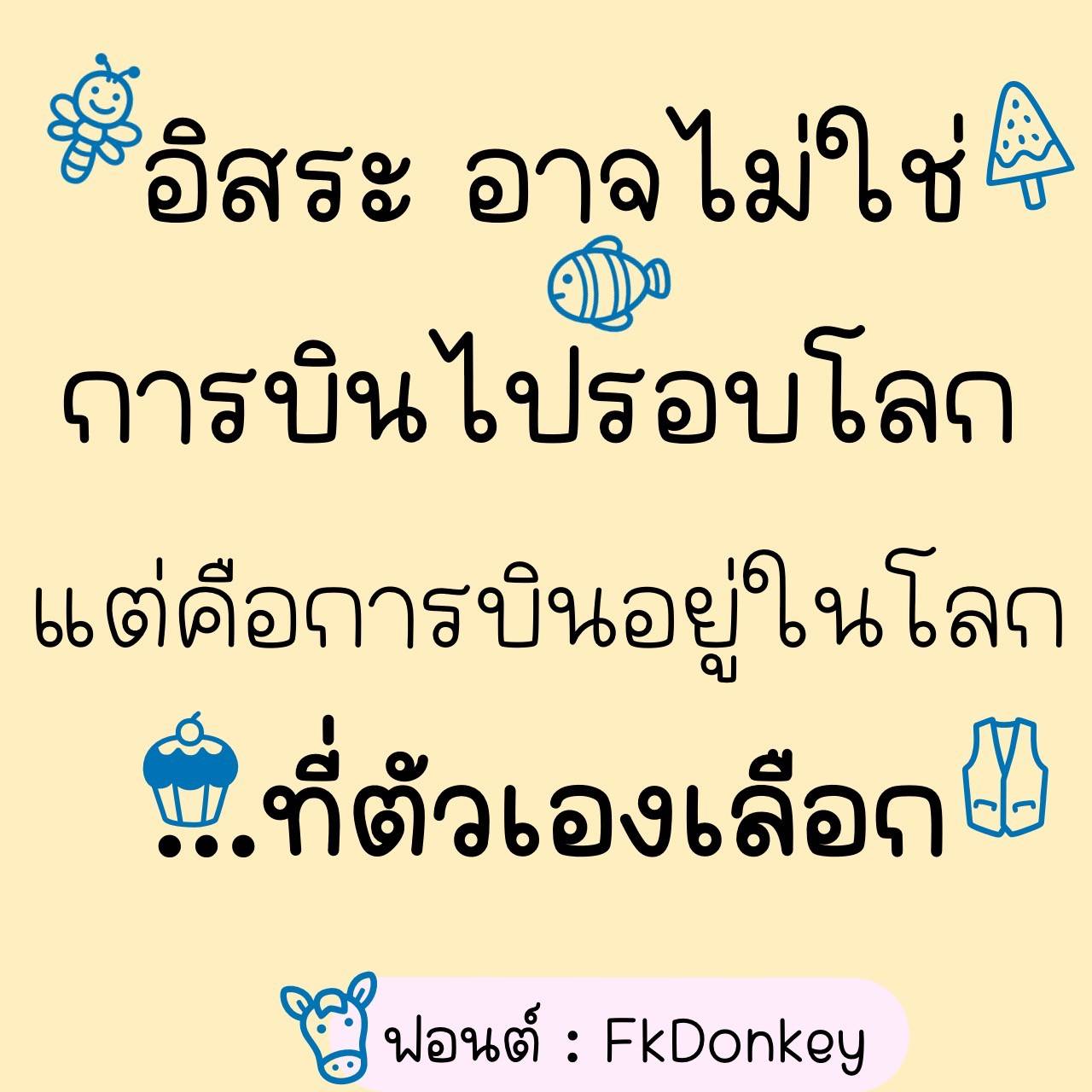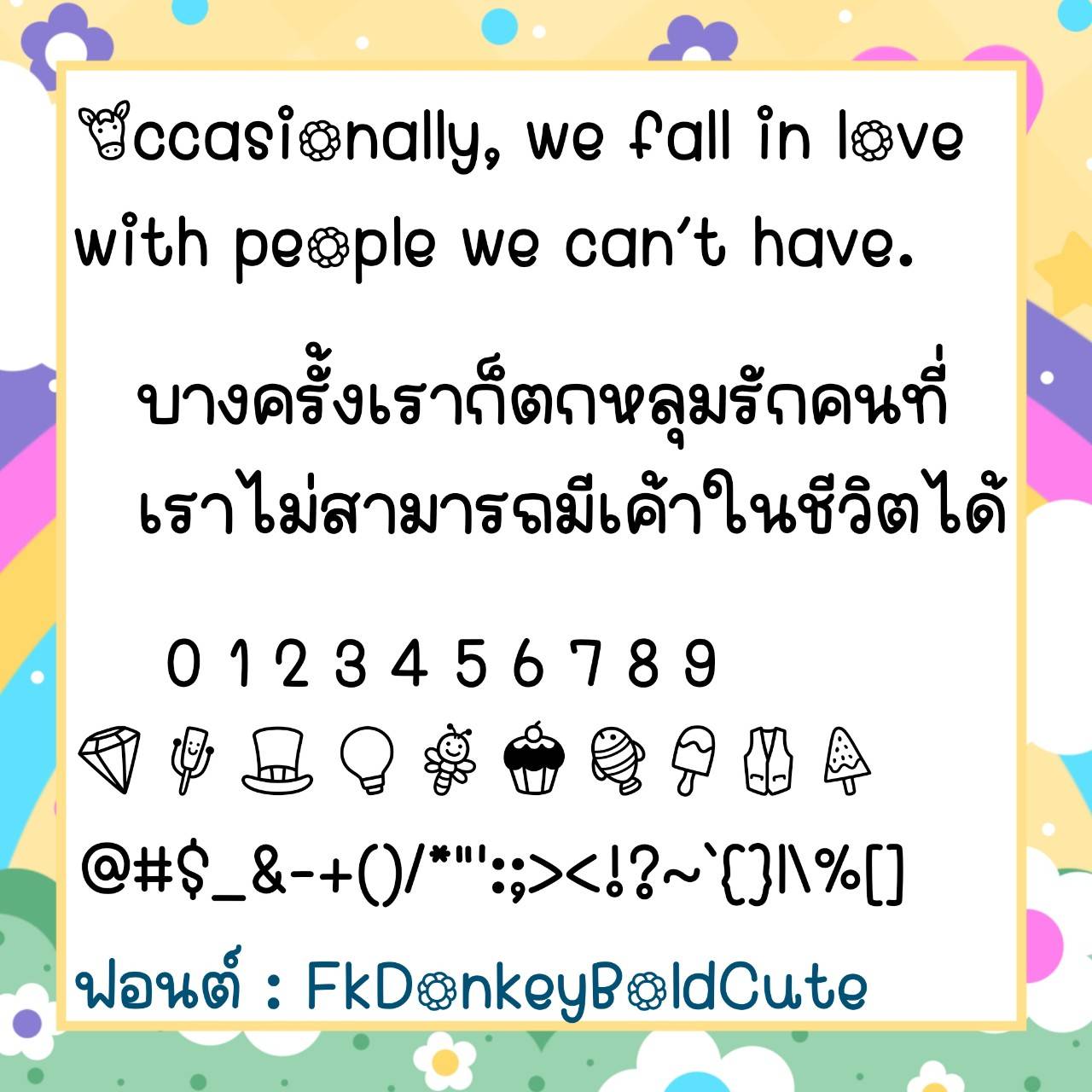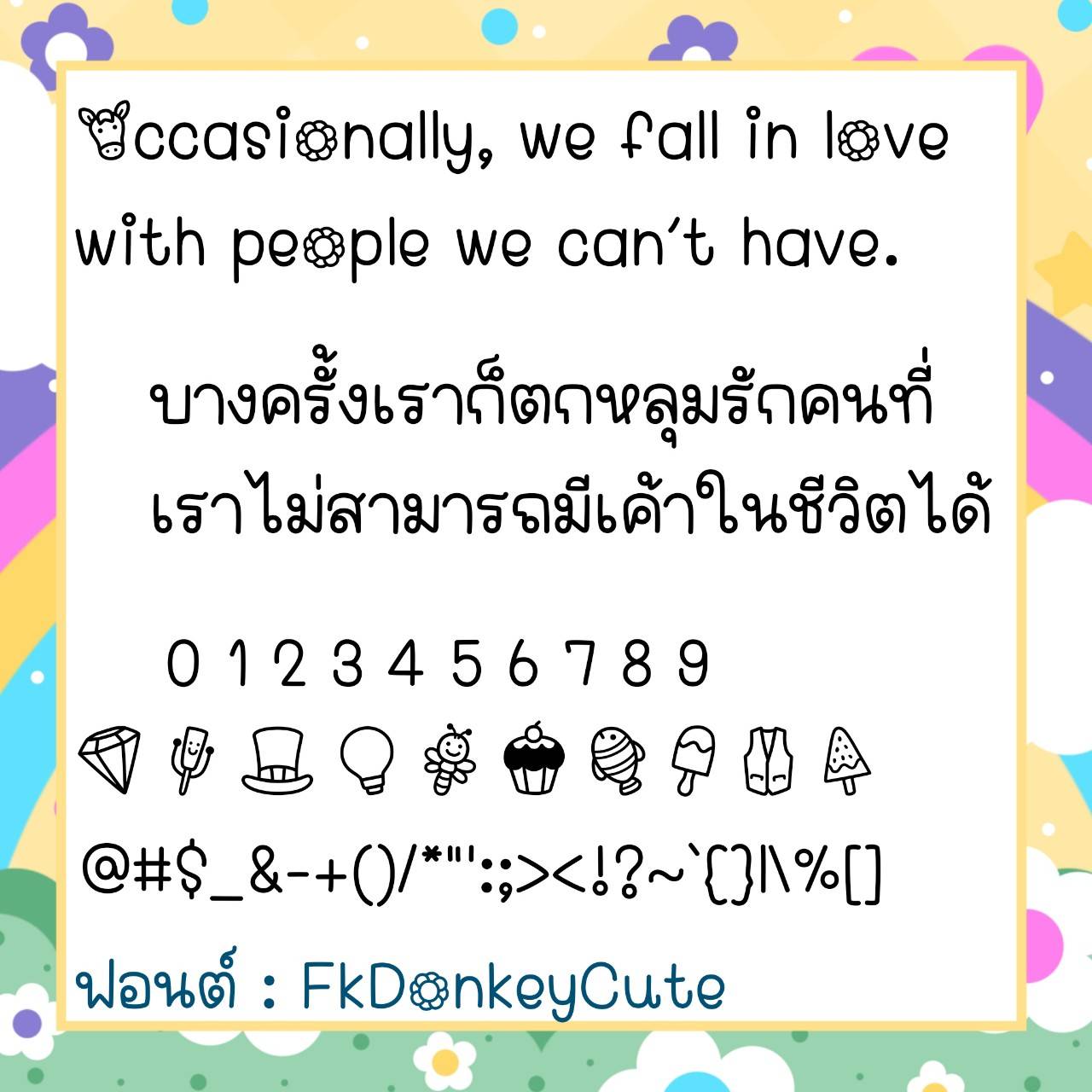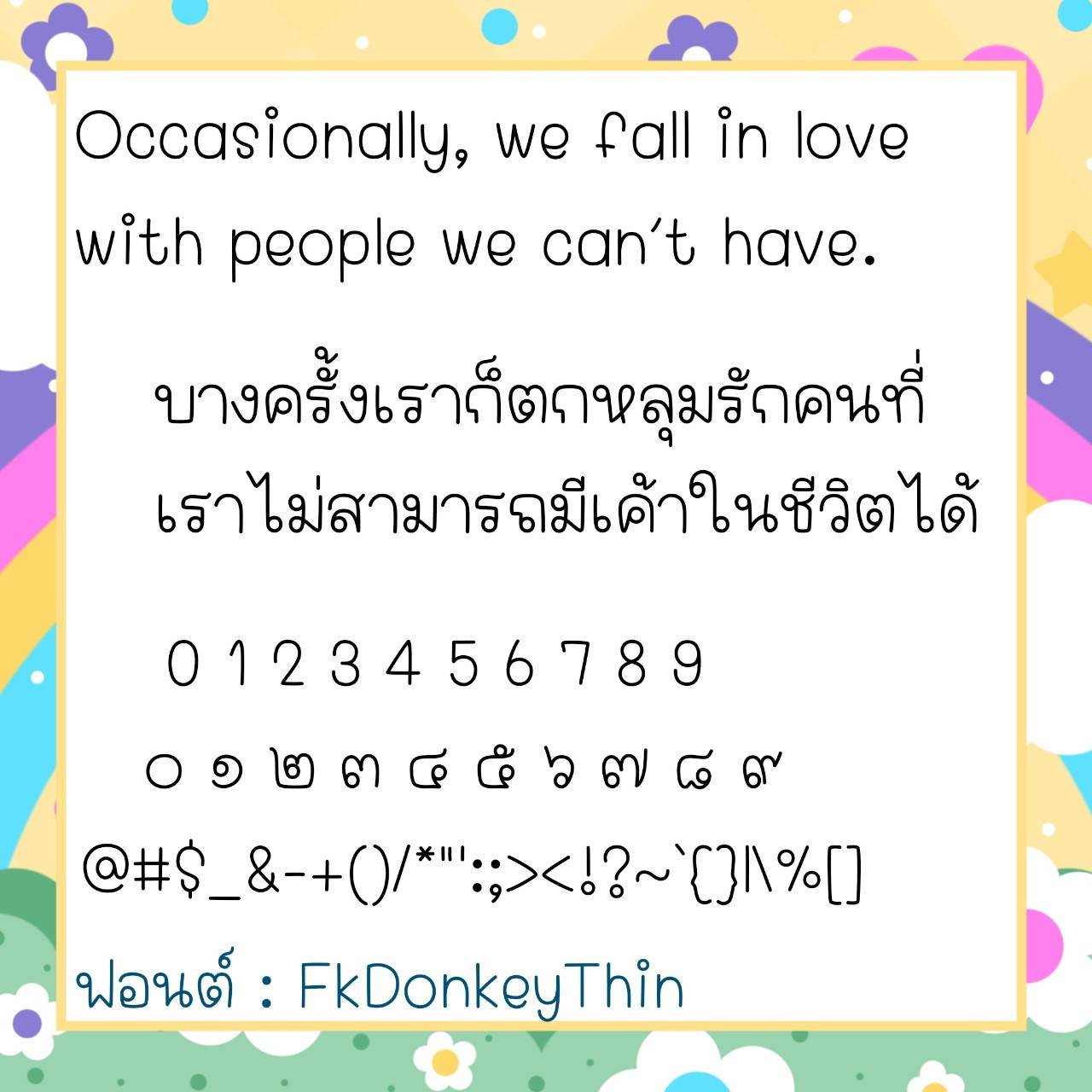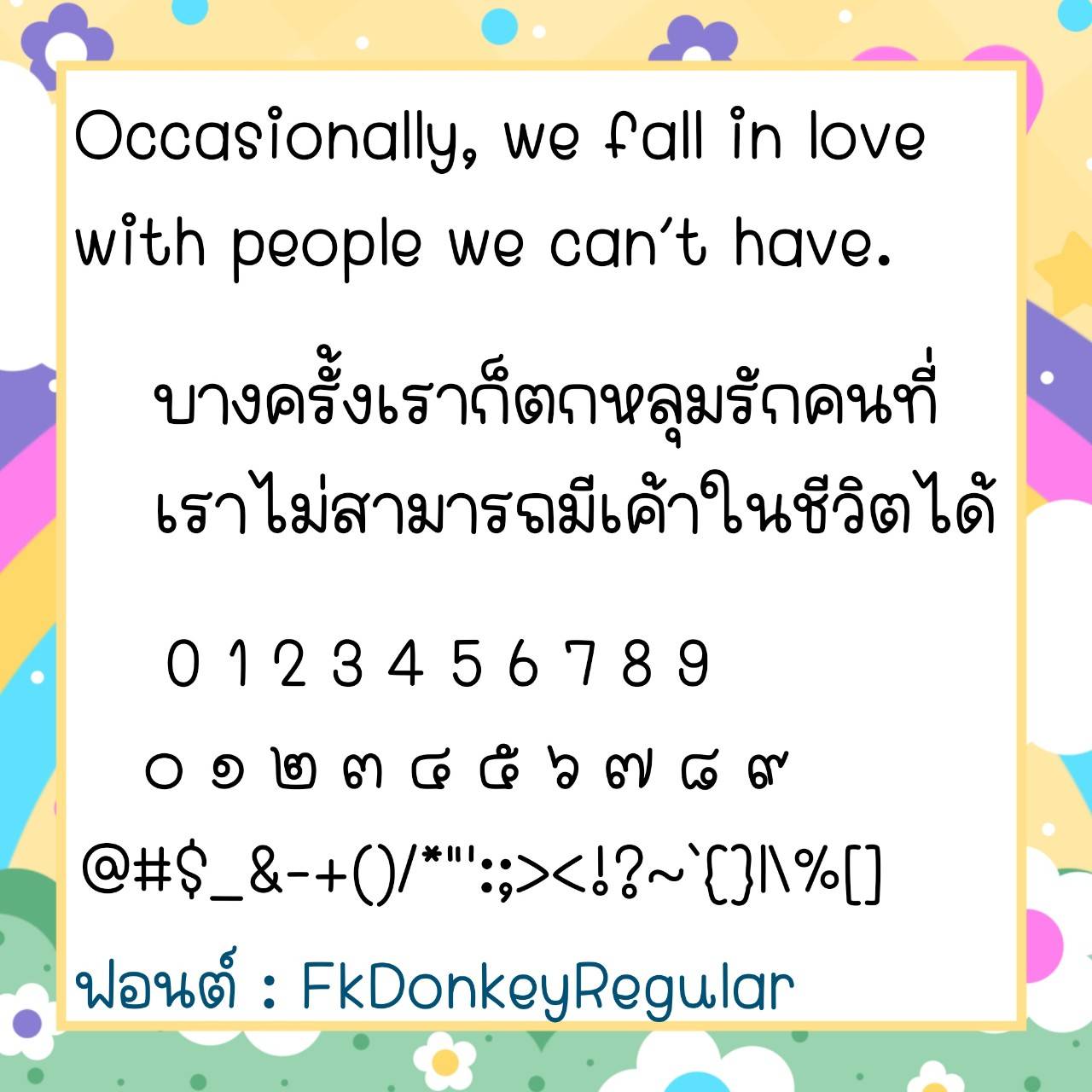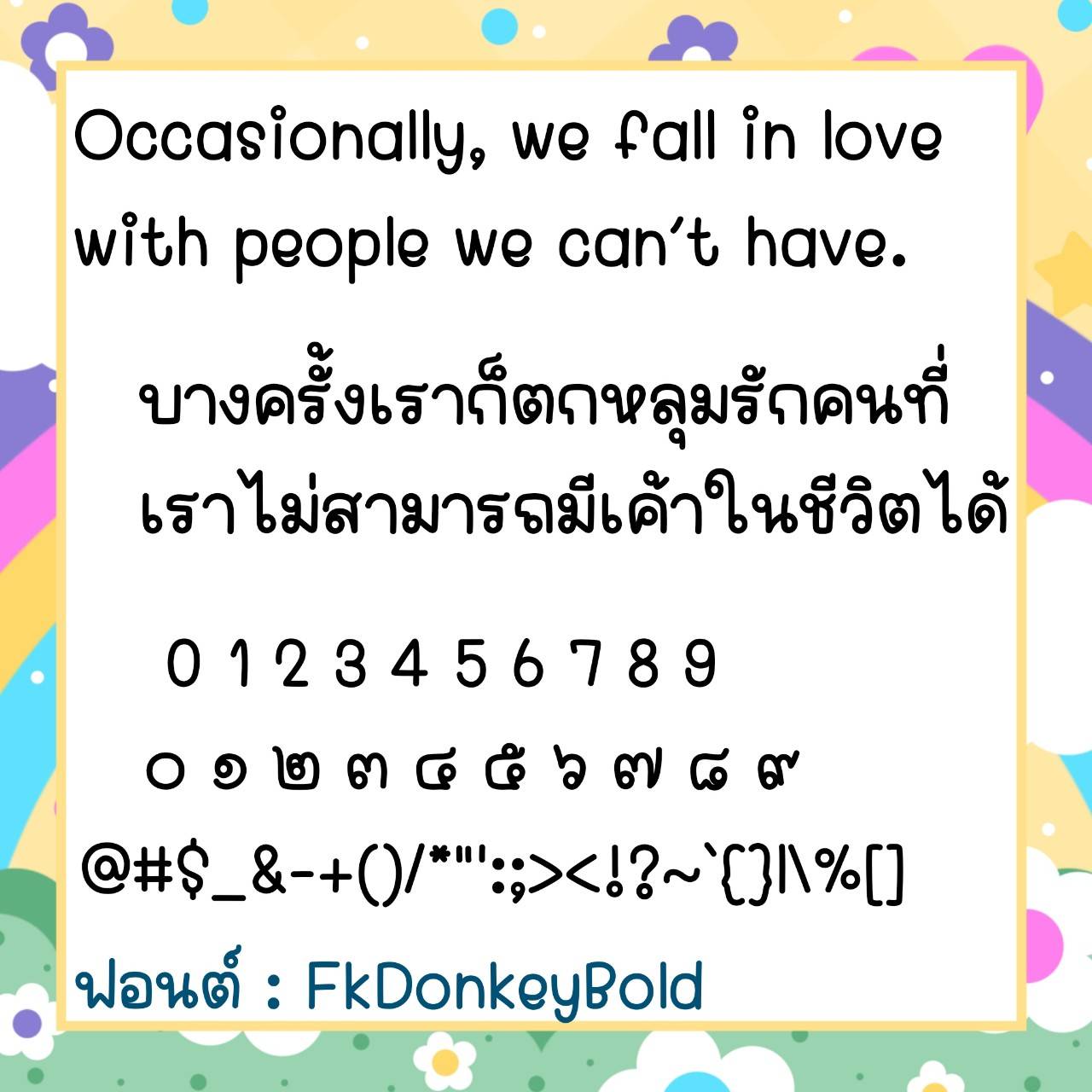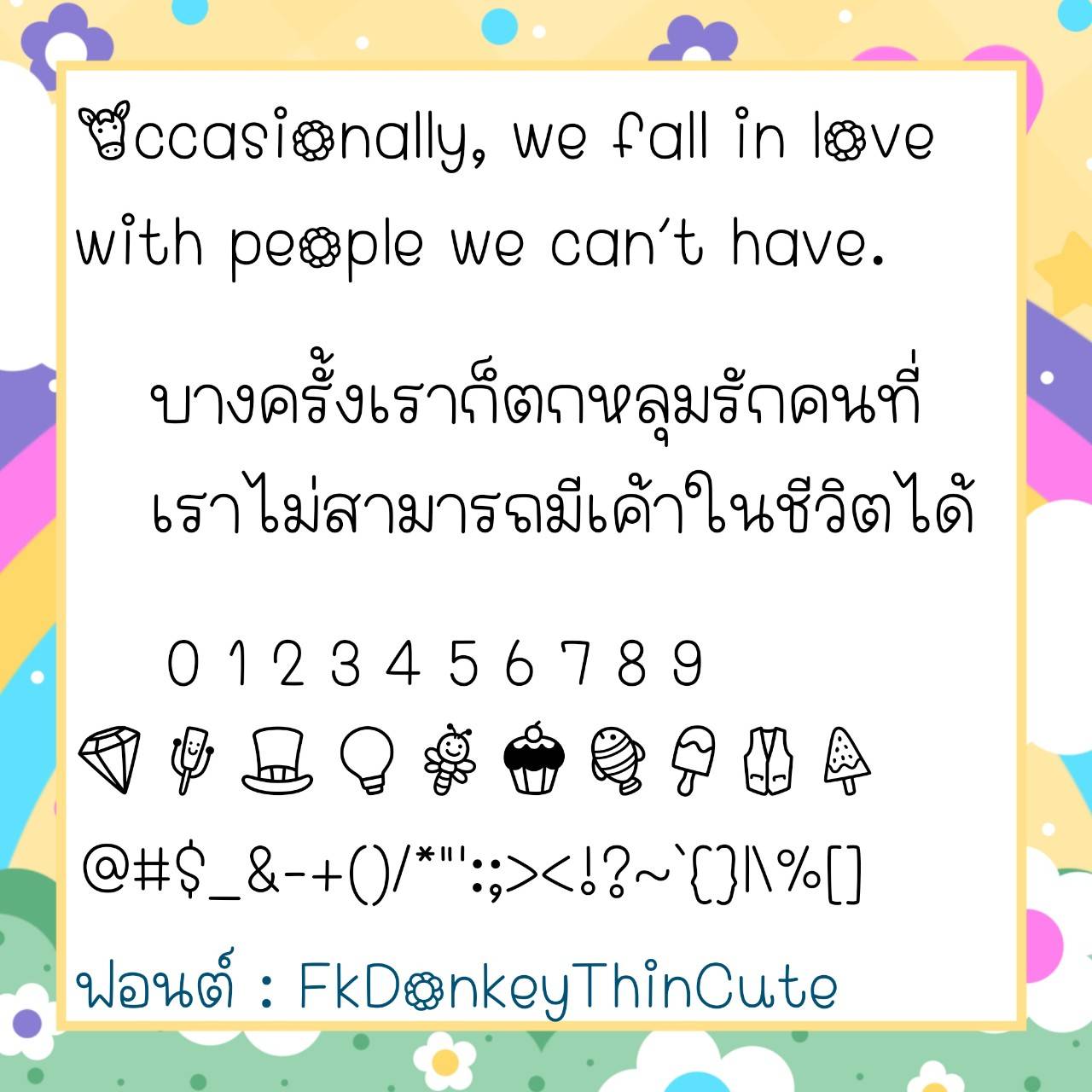
Font FkDonkey
🔸 ฟอนต์ลายมือแนวน่ารัก ดูมีความวัยรุ่นนิดๆ ขนาดฟอนต์อวบอ้วน อ่านง่ายสบายตามากๆ และยังมีไฟล์อิโมจิน่ารักๆ ที่ใช้แทนเลขไทยให้ด้วยค่ะ 🥰💙
🔹 A cute handwritten font that looks a bit youthful. The font size is plump and easy to read. It also has a cute emoji file that can be used to replace Thai numerals. 🥰💙